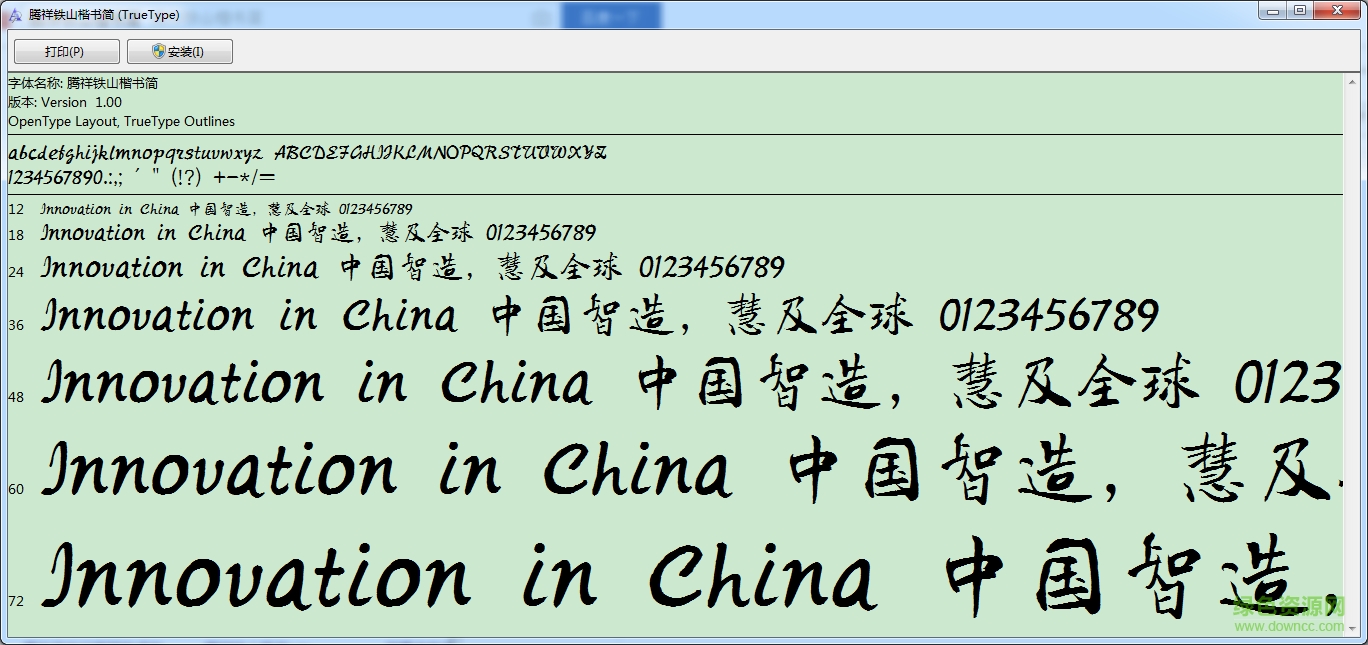
軟件介紹 軟件標(biāo)簽: 騰祥字體 字體 騰祥鐵山楷書簡是一款非常的優(yōu)雅的楷體字體,這款字體筆鋒細(xì)膩,看上去十分美觀。喜歡這款字體的朋友歡迎來綠色資源網(wǎng)下載使用。騰祥鐵山楷書簡字體安裝方法方法一:控制面板/字體/文件/安裝新字體;方法二:直接將字體復(fù)制到C:\WINDOWS\Fonts。方法三:針對win7系統(tǒng),用戶只需選中字體右鍵安裝即可。注意事項本站所有字體資源僅供個人學(xué)習(xí)與參考,如需商業(yè)使用請到相關(guān)官網(wǎng)授權(quán)。 軟件截圖 上一張下一張(1 / 1) 安裝詳細(xì)截圖 猜你喜歡 騰祥字體 楷書字體 騰祥字體 騰祥字體(Tensentype)是由騰祥公司推出的一系列字體合集,開發(fā)推出了多款特色字體,如:騰祥嘉麗中黑簡、騰祥金磚黑簡、騰祥潮黑等,每款字體都很有特點,獨具個性,深受廣大朋友們的喜愛。 查看更多>> 騰祥豆豆體簡繁 8.78M/中文/5.0/v1.0 pd端下載 騰祥泡泡體ttf 5.89M/中文/5.0/下載 tensentype chaoheij字體 1.34M/中文/5.0/下載 tensentype xiangsif 2.44M/中文/5.0/下載 tensentype jinzhuanheij 2.44M/中文/3.3/下載 騰祥匆匆體繁 4.98M/中文/5.0/下載 楷書字體 楷書字體是綠色資源網(wǎng)小編專為大家收集的一類非常流行而且好用的楷書字體,它包括了各種形式的楷書??瑫步姓?、真書、正書。從程邈創(chuàng)立的隸書逐漸演變而來,更趨簡化,橫平豎直,筆勢雄奇,姿態(tài)橫生,可應(yīng)用于繪畫設(shè)計、藝術(shù)創(chuàng)作、平面廣告、印刷包裝、電視廣告等等各行各業(yè)。也是現(xiàn)在很多行業(yè)必用的一類字體,小編收集的這一類楷書字體希望能更好的幫助大家收集和使用楷書字體。 查看更多>> 楷體國標(biāo)字體官方版 2.45M/中文/7.1/下載 漢儀閃耀楷書字體 1.77M/中文/0.0/下載 華為漢儀錦時楷書 2.92M/中文/5.0/下載 楷書字典手機版 4.46M/中文/5.0/v2.0 安卓版下載 經(jīng)典楷體繁體 3.96M/中文/5.0/下載 楷書繁體字體包 9.76M/中文/8.0/下載 其他版本下載 標(biāo)題 大小 更新日期 下載 下載地址 電腦版 騰祥鐵山楷書簡字體 點擊報錯 軟件無法下載或下載后無法使用,請點擊報錯,謝謝! 關(guān)閉報錯反饋 請描述您所遇到的錯誤,我們將盡快予以修正,謝謝! *必填項,請輸入內(nèi)容 本類最新 dreamweaver字體庫 首爾南山體字體 v1.06 官方版 潮字社風(fēng)云簡ttf 潮字社凌渡鯤鵬簡體字體 潮字社曾玉波手書簡字體 微博慧心字體 相關(guān)文章 Photoshop字體安裝使用方法和技巧 如何解決“無法新增字體”問題 Win 7系統(tǒng)安裝字體方法 網(wǎng)頁字體大小設(shè)置方法 怎么改網(wǎng)頁字體大小 在Linux系統(tǒng)中安裝字體的幾種方法 windows7字體顯示問題:打開某些程序的時候顯示的是亂碼 用戶評論 熱門評論 最新評論 發(fā)表評論 查看所有評論(0) 昵稱: 請不要評論無意義或臟話,我們所有評論會有人工審核. 字?jǐn)?shù): 0/500 (您的評論需要經(jīng)過審核才能顯示)